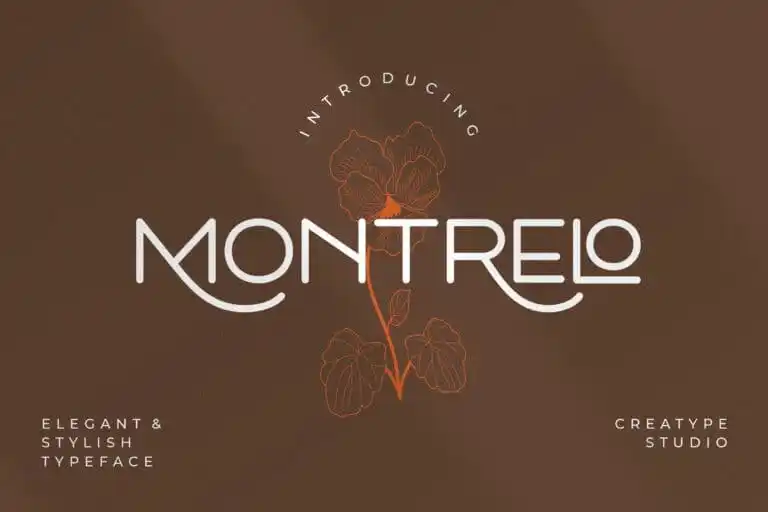
A Montrelo Sans Serif é uma tipografia moderna e elegante criada pelo Creatype Studio. Este tipo se destaca por sua sofisticação e elegância, adaptando-se perfeitamente tanto para pequenos detalhes quanto para grandes tamanhos de texto. Seu design versátil permite aplicá-lo em uma variedade de contextos, tornando-o um recurso valioso para designers que procuram transmitir modernidade e classe em seus projetos visuais. A Montrelo é ideal para usar em websites, sites de mídia social ou até mesmo em logotipos – sua linguagem limpa e moderna faz com que a informação seja centralizada e clara, tornando-a uma excelente opção para qualquer aplicação visual contemporânea.